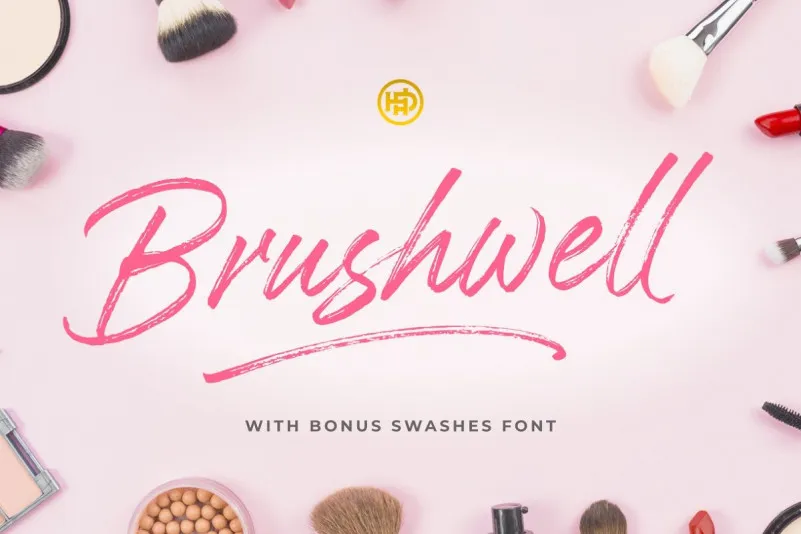
Brushwell Dry Brush Font – Download Grátis
Introduzimos a Brushwell Font! Ela foi criada e compartilhada por Hendra Pratama. É uma fonte de escrita feita à mão moderna com traços secos rápidos. Esta font permite criar o efeito de pincel desbotado, que fornece um aspecto natural às belas escrituras feitas a mão do estilo da caligrafia. A Brushwell é perfeitamente adequada para uso em revistas, cabeçalhos, postais, capas de álbum, embalagens, design de logotipos, catálogos e marcações. Se você está procurando uma fonte que ofereça um estilo elegante e autêntico sem comprometer a velocidade de criação, a Brushwell pode ser sua escolha perfeita. Esta font é ideal para designers gráficos que buscam criar visualmente impactantes e atraentes para seus projetos, especialmente em mídias onde o detalhe e o aspecto natural contam muito. Seja em um design de logotipo respeitosamente contemporâneo ou em uma capa de álbum elegante, a Brushwell oferece as ferramentas perfeitas para tornar suas ideias únicas mais atraentes e eficazes.